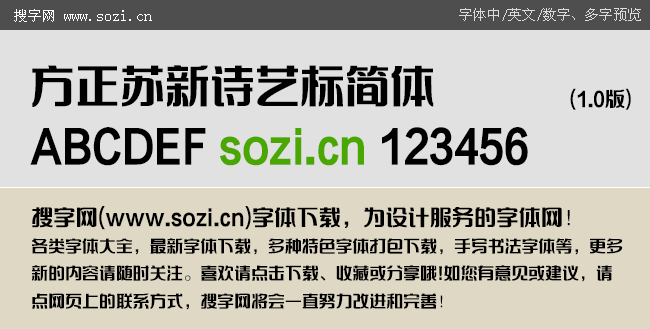
方正蘇新詩(shī)藝標(biāo)簡(jiǎn)體
搜字網(wǎng)提供一款非常藝術(shù)的方正蘇新詩(shī)藝標(biāo)簡(jiǎn)體下載,方正蘇新詩(shī)藝標(biāo)簡(jiǎn)體是一款以綜藝體為原形進(jìn)行藝術(shù)設(shè)計(jì)的字體,該字體極具藝術(shù)感,簡(jiǎn)潔大方,適用于包裝印刷、廣告設(shè)計(jì)、平面設(shè)計(jì)、書籍報(bào)紙等領(lǐng)域。